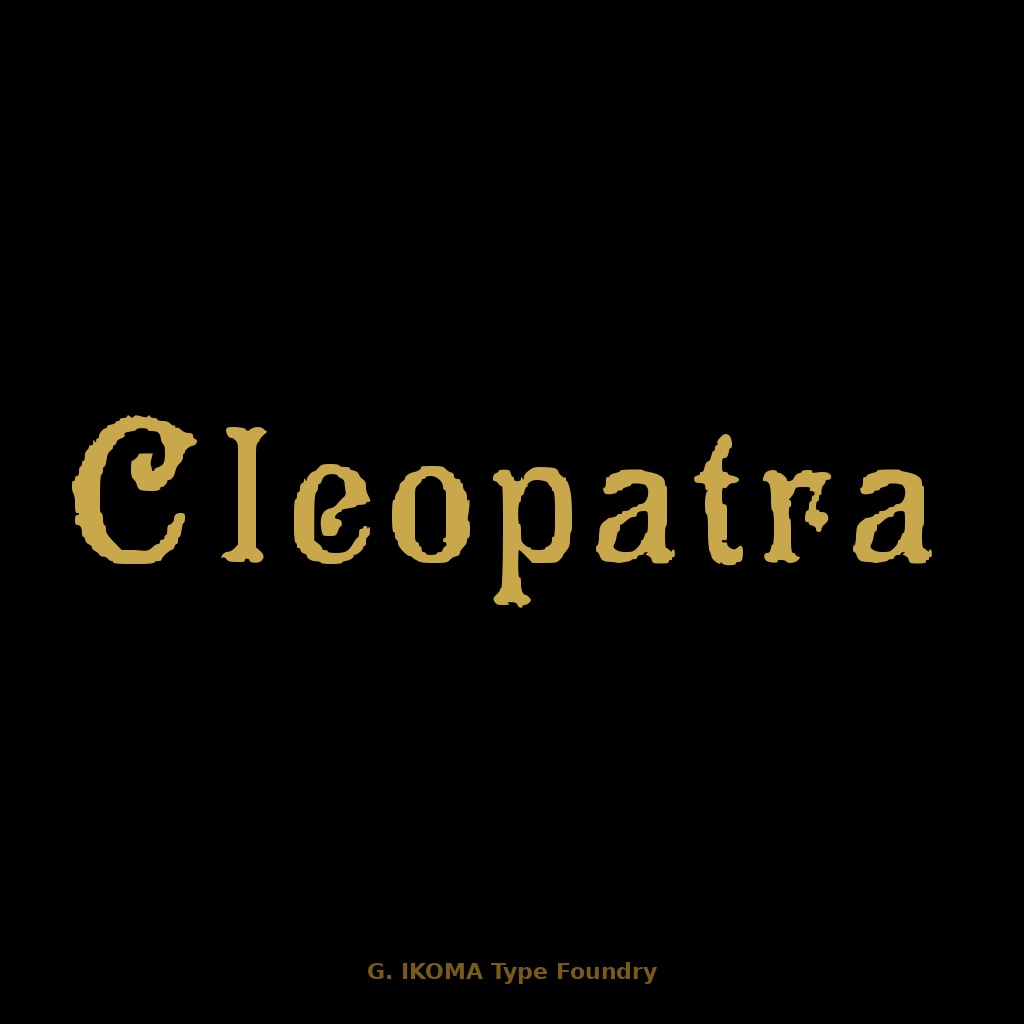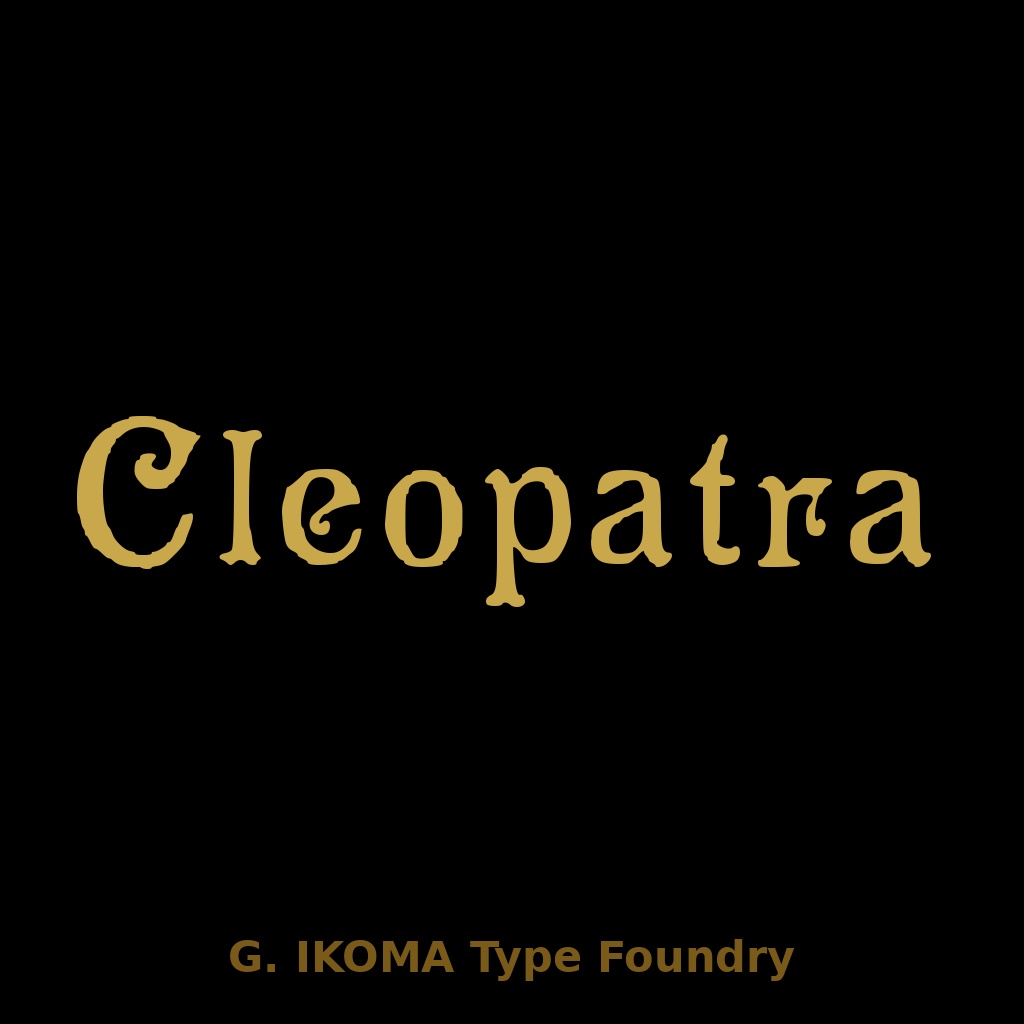
Cleopatra — ヴィクトリア朝装飾欧文フォント / Victorian Display Typeface [Decorative Antique Serif]
━━━━━━━━━━━━━━━━━━━━━━━━━ 【フォントについて】 ━━━━━━━━━━━━━━━━━━━━━━━━━ Cleopatra は、19世紀末〜20世紀初頭の欧州印刷資料を原典に、 手作業でトレース・デジタル化した復元フォントです。 ロンドンの名門活字鋳造所 H. W. Caslon & Co. が制作した同名書体をもとに デジタル再構成した作品です。 大文字はスクリプト的な流れを持ちながら強いセリフで締まる独特のフォルム、 小文字はオールドスタイルローマン体の温かみと活字版的な存在感を持ちます。 ヴィクトリア朝印刷物特有の格調と装飾性を現代のデジタル制作に持ち込める書体です。 原典:Ludwig Petzendorfer, "Schriften-Atlas" / Julius Hoffmann, Stuttgart(パブリックドメイン) 様式:Victorian Display / Decorative Antique Serif 収録グリフ:62文字(A–Z / a–z / 0–9)+記号多数(計94グリフ) 欠落グリフ:なし 制作:株式会社生駒時計店 / G. IKOMA, LTD.(1870年創業) ━━━━━━━━━━━━━━━━━━━━━━━━━ 【ご購入前にご確認ください】 ━━━━━━━━━━━━━━━━━━━━━━━━━ 本フォントはヴィクトリア朝様式を特徴とするディスプレイ向け装飾書体です。 ロゴ・見出し・装飾用途に適していますが、本文組版や小サイズでの長文には向きません。 特に大文字にスクリプト的な曲線があり、独特の字形を持ちます。ご購入前にthumb2の グリフチャートで文字形をご確認ください。 ━━━━━━━━━━━━━━━━━━━━━━━━━ 【収録内容】 ━━━━━━━━━━━━━━━━━━━━━━━━━ ・I_Cleopatra_Extended.ttf ・LICENSE.txt(日英) ━━━━━━━━━━━━━━━━━━━━━━━━━ 【推奨用途】 ━━━━━━━━━━━━━━━━━━━━━━━━━ ・ロゴ・ブランド名 ・書籍・同人誌のタイトル・章タイトル ・ゲームのUI・タイトル画面 ・アンティーク・ヴィンテージテイストのデザイン ・ヴィクトリア朝・エドワード朝テーマのデザイン ・ポスター・フライヤーの見出し ・SNSアイコン・バナー・動画サムネイル 19世紀末ロンドン活字文化の格調を持つ、装飾性と可読性を兼ね備えた欧文書体です。 本文組版・小サイズでの常用には向きません。 ━━━━━━━━━━━━━━━━━━━━━━━━━ 【ライセンス】 ━━━━━━━━━━━━━━━━━━━━━━━━━ 本フォントは、個人利用・商用利用を問わず、印刷物、画像、ロゴ、バナー、 動画サムネイル等の制作に使用できます。 また、WebサイトやSNSで画像化された状態で使用することは可能です。 ただし、以下の行為は禁止します。 ・フォントファイルそのものの再配布、再販売、譲渡、共有 ・改変したフォントファイルの配布 ・本フォントを素材集、テンプレート、デジタル商品等に収録して再販売する行為 ・本フォントファイルをWebフォントとしてサーバーに設置・配信して利用する行為 ・アプリケーション、ゲーム、ソフトウェア、電子機器等への埋め込み利用 ・AI学習、機械学習、生成モデル訓練等への利用 ・本フォント自体または収録字形そのものについて独占的権利を主張する行為 詳細は同梱の LICENSE.txt をご確認ください。 ━━━━━━━━━━━━━━━━━━━━━━━━━ 【原典資料について】 ━━━━━━━━━━━━━━━━━━━━━━━━━ 本フォントは、G. IKOMA, LTD. 所蔵の実物資料をもとに制作しています。 原典資料そのものは本商品に含まれていません。 資料アーカイブについては、下記サイトをご参照ください。 G. IKOMA Archive https://g-ikoma-archive.netlify.app/ ━━━━━━━━━━━━━━━━━━━━━━━━━ BOOTH: https://g-ikoma.booth.pm/